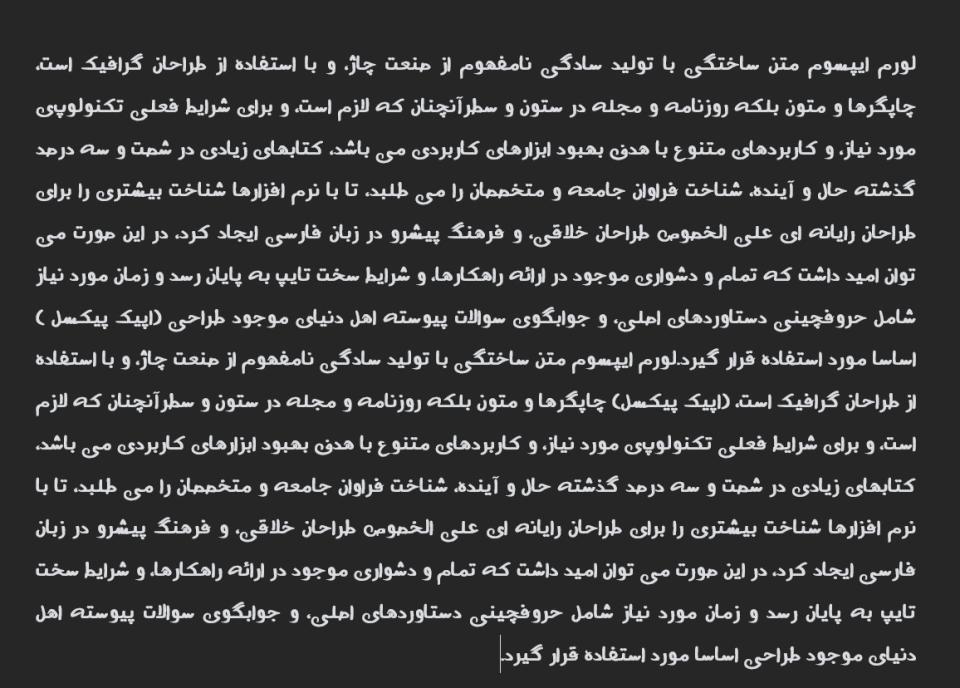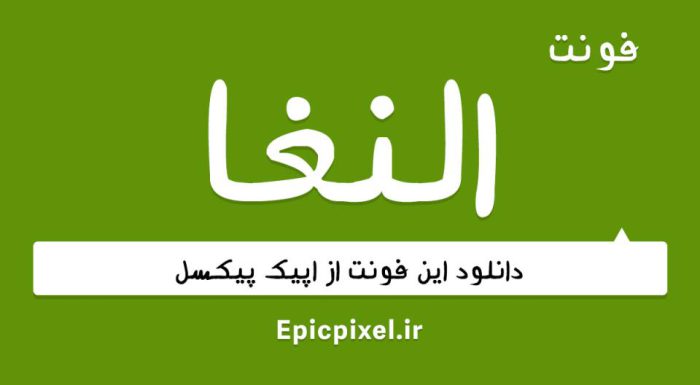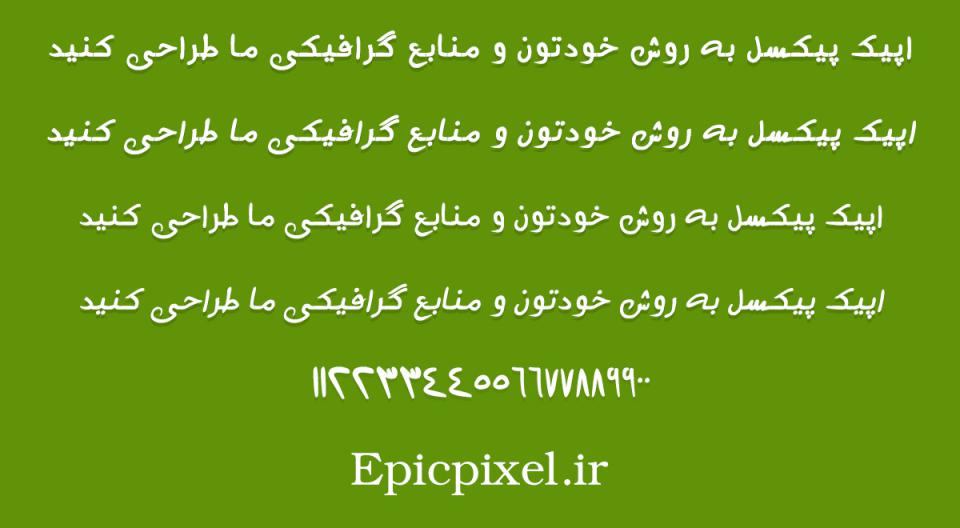
فونت النغا فارسی، با ظاهری کودکانه و دست نویس، حس صمیمیت و خودمانی بودن را به مخاطب القا می کند. این فونت، با حروف کج و معوج و خطوط نرم، یادآور نوشته های دوران کودکی است و می تواند برای پروژه هایی که نیاز به فضایی شاد، دوستانه و غیررسمی دارند، انتخابی ایده آل باشد. تصور کنید برای طراحی جلد یک کتاب کودک، کارت دعوت تولد یا حتی یک پست در شبکه های اجتماعی با موضوعی سرگرم کننده، به دنبال فونتی هستید که حس اصالت و دست ساز بودن را منتقل کند؛ النغا دقیقاً همان چیزی است که به آن نیاز دارید.
یکی از ویژگی های بارز النغا، خوانایی بالای آن در عین سادگی است. حروف به گونه ای طراحی شده اند که حتی در اندازه های کوچک نیز به راحتی قابل تشخیص باشند. این ویژگی، النغا را برای استفاده در متن های کوتاه، عناوین و حتی بسته بندی محصولات مناسب می سازد. البته، به دلیل ظاهر خاص و غیررسمی اش، ممکن است برای متن های طولانی یا پروژه های رسمی و اداری چندان مناسب نباشد.
اگر به دنبال فونتی هستید که حس نوستالژی، صمیمیت و بازیگوشی را در مخاطب زنده کند، النغا انتخابی هوشمندانه است. این فونت، با ظاهر منحصربه فرد خود، می تواند به پروژه های شما، هویتی خاص و متمایز ببخشد و آن ها را از سایر آثار، متمایز سازد.
| ⭐ توضیحات | فونت اصلاح شده عربی النغا |